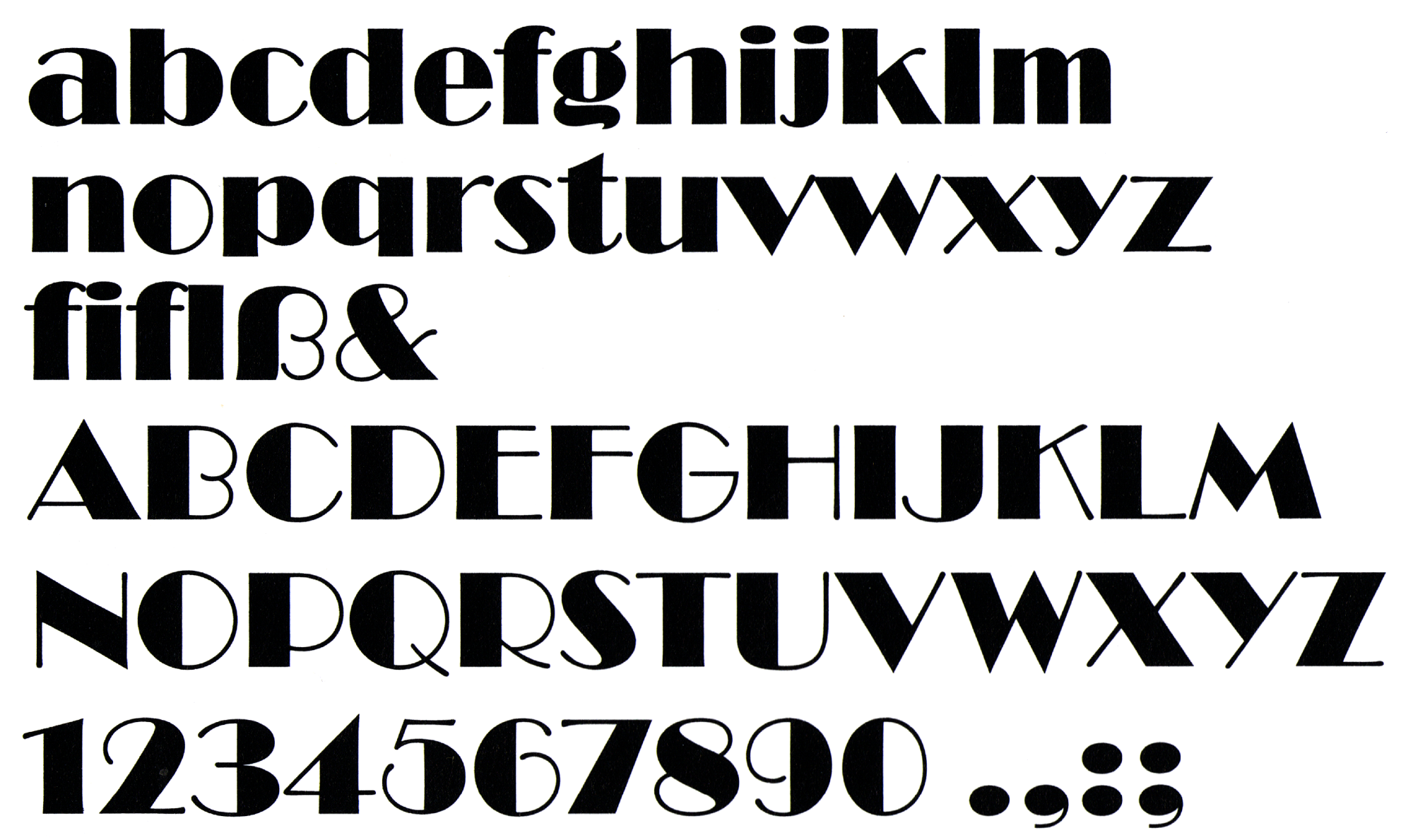
- 1927
- Antiqua dekorativ
Die Broadway zählt zu den bekanntesten Art-Deco-Schriften. Sie erschien zunächst in einer Zeichnung von Morris Fuller Benton als reines Versal-Alphabet bei American Type Founders. Sol Hess baute die Schrift zwei Jahre später zu einer zweihäusigen Schrift aus und ergänzte ein lichte Version.
Digitalisierungen sind heute von zahlreichen Anbietern erhältlich. Monotype bietet einen umfangreichen Zeichenausbau in der Pro-Version. Die URW-Version bietet Schnitte, die es in der Originalversion nicht gab (Compress, Outline, Stencil).